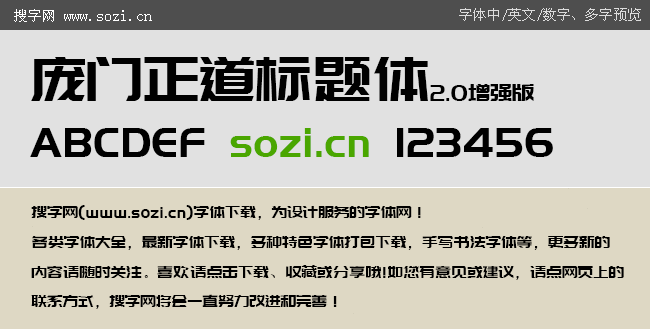
龐門正道標題體2.0增強版
搜字網提供一款龐門正道標題體2.0增強版中文字體下載,龐門正道標題體是一款知名設計博主阿門推出據稱耗資超10W的字體,并且是永久免費授權商用。整體字形筆畫均衡,風格現代,字體方中帶圓,端莊雅致,簡約時尚。本作品適用于胖體設計字體、標題設計字體、品牌設計字體、動漫設計字體等應用。